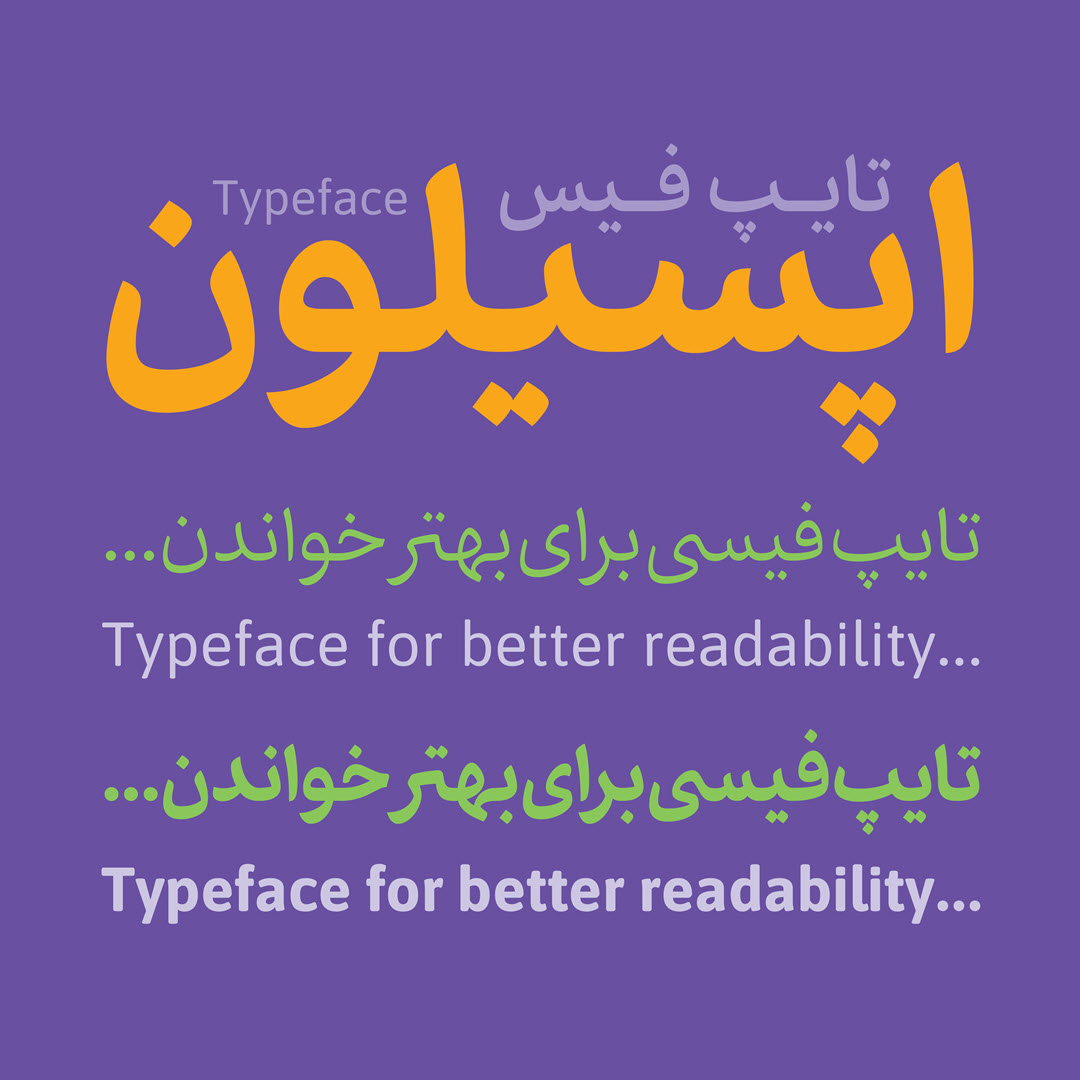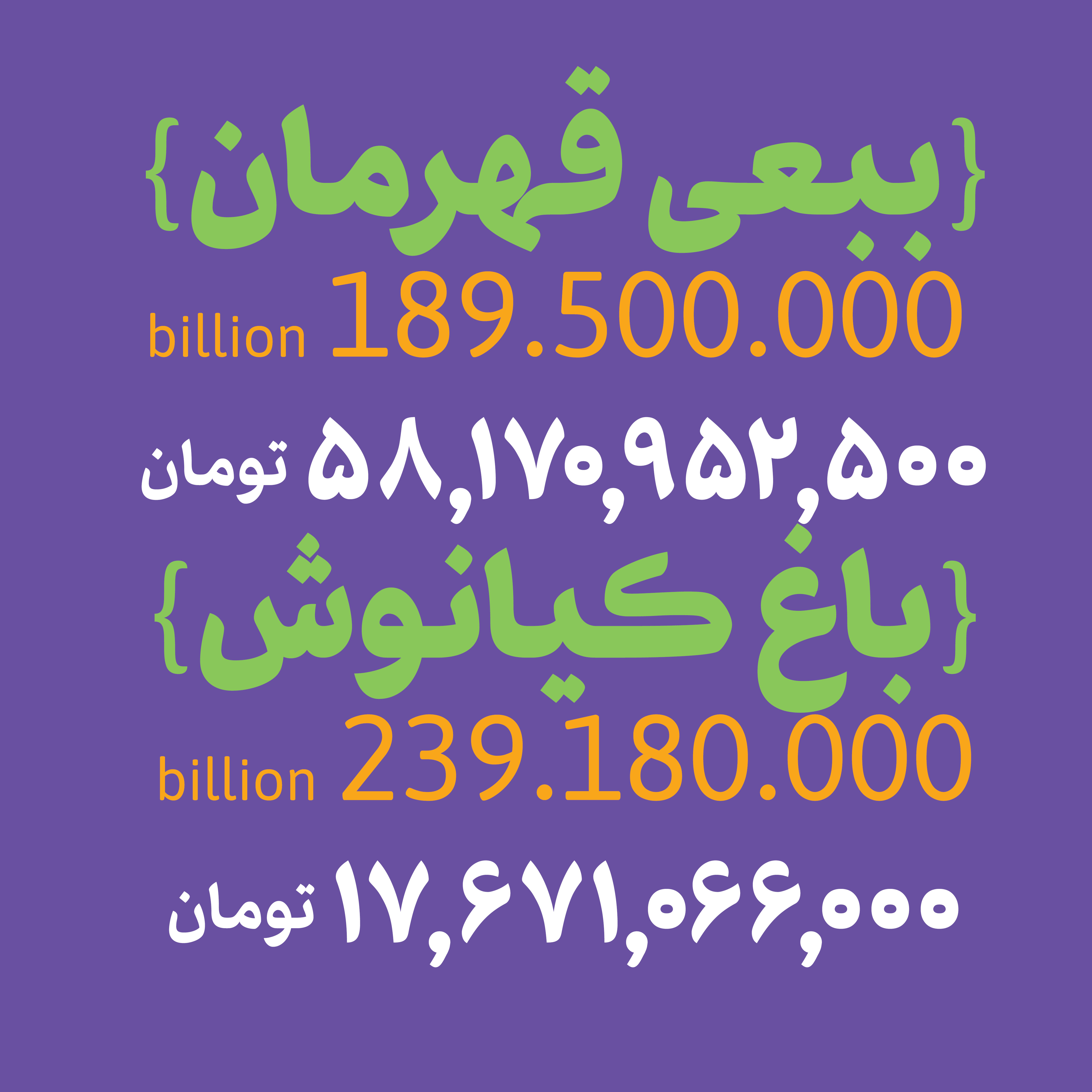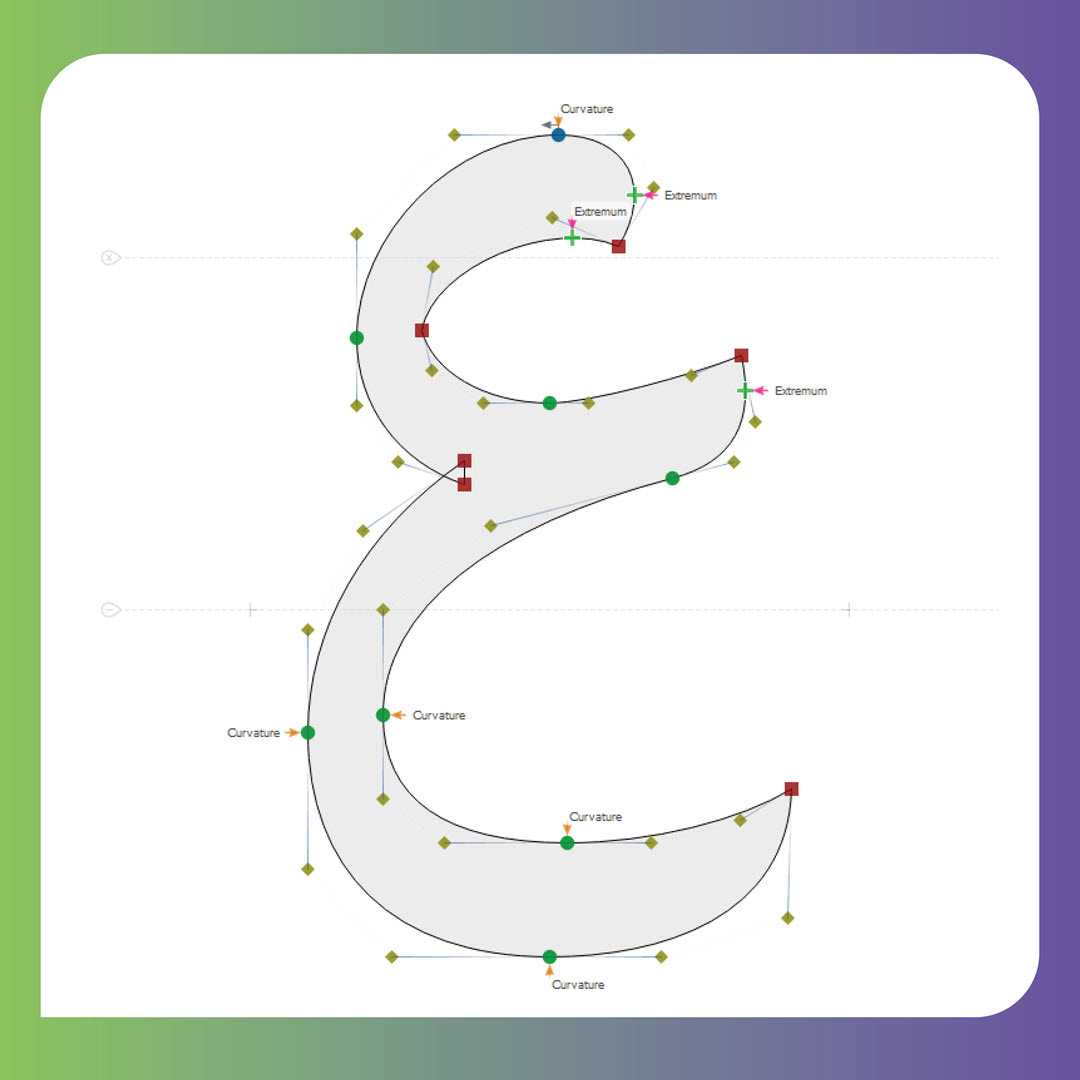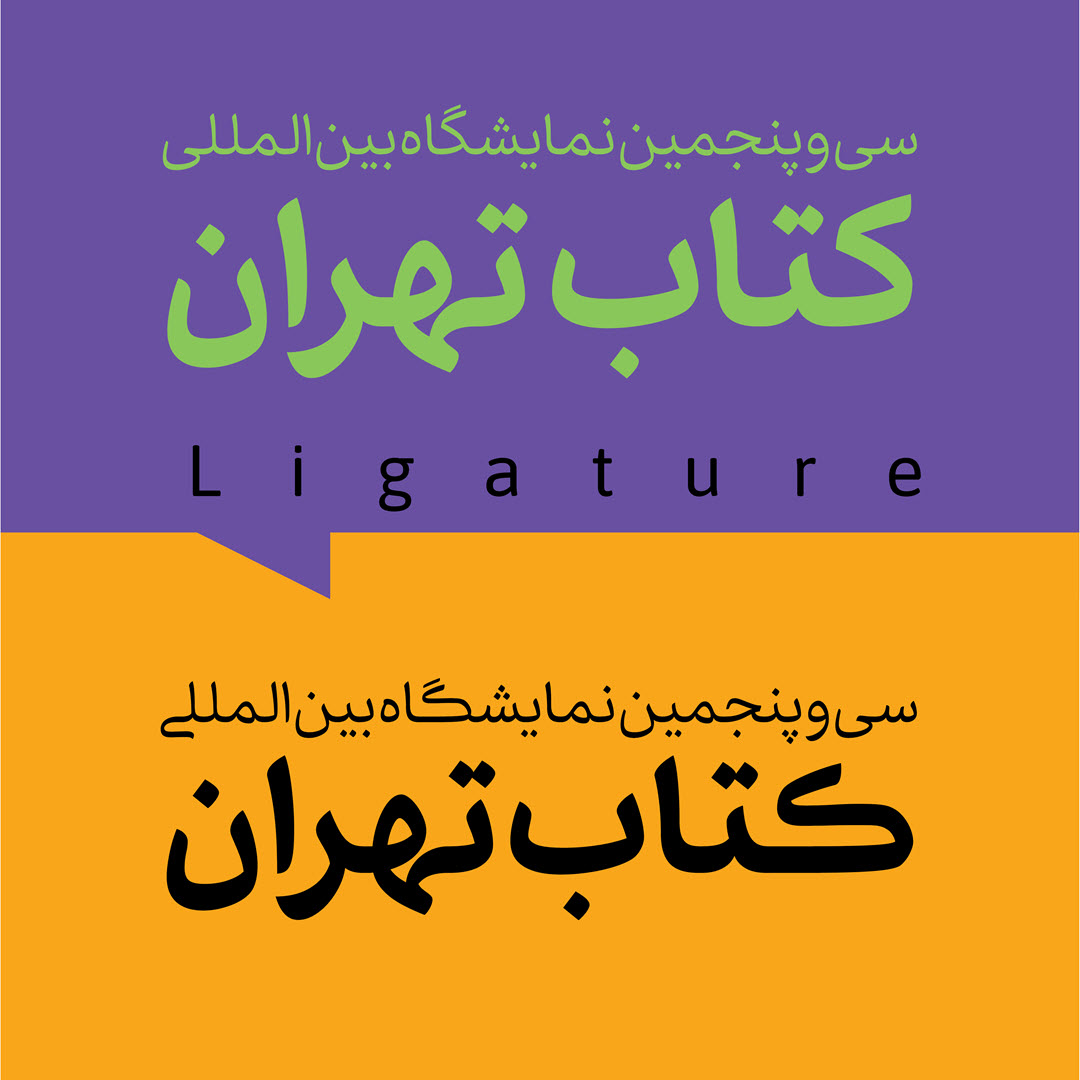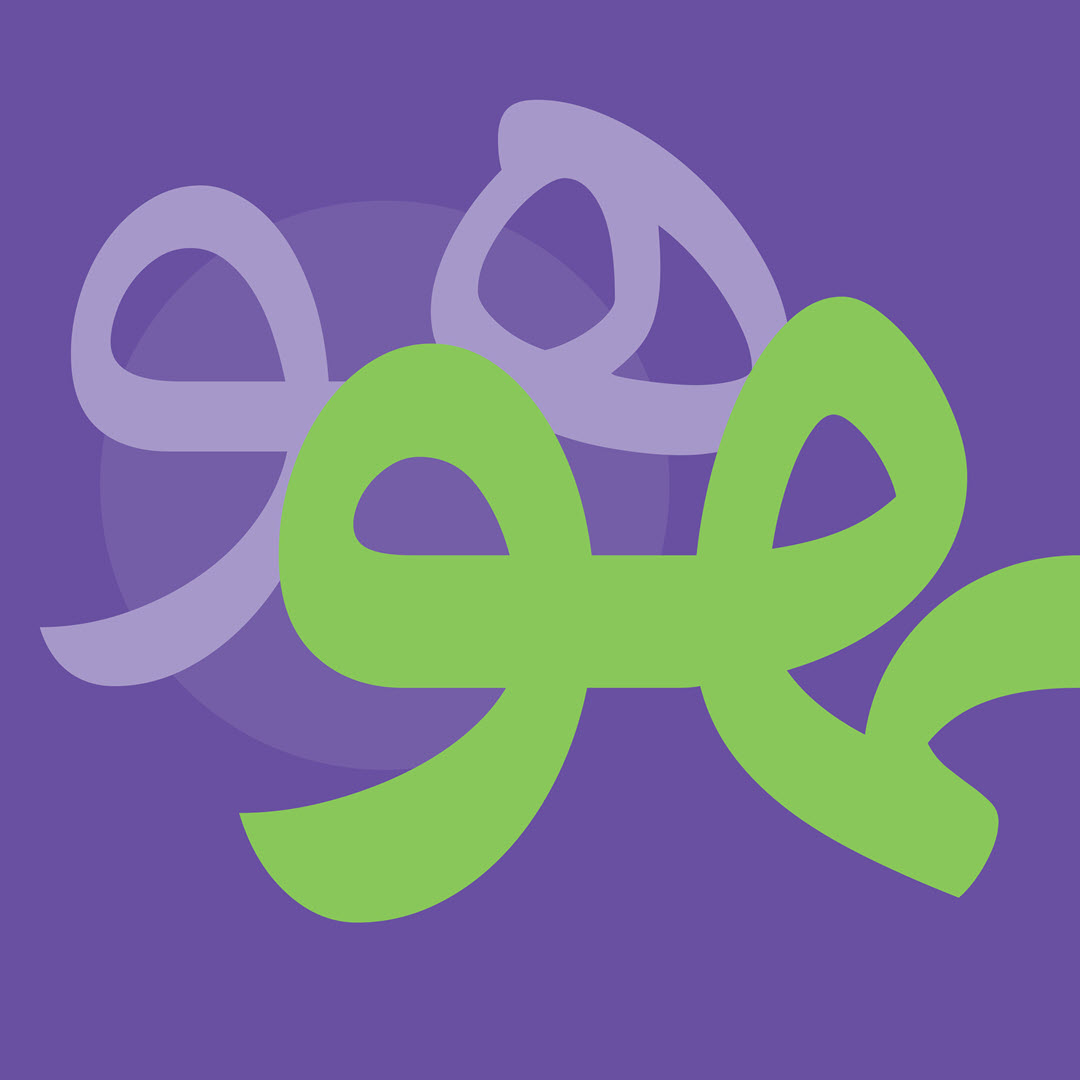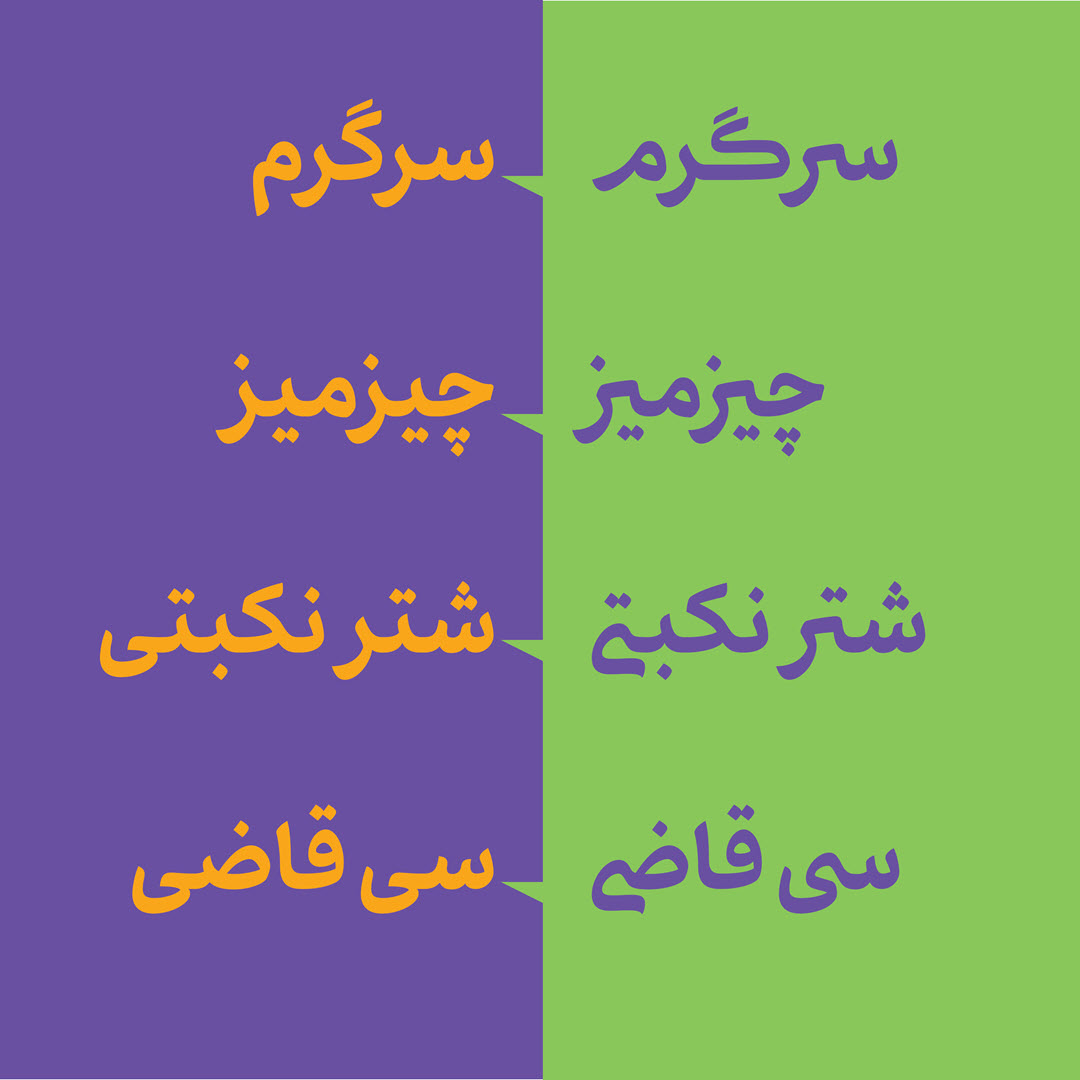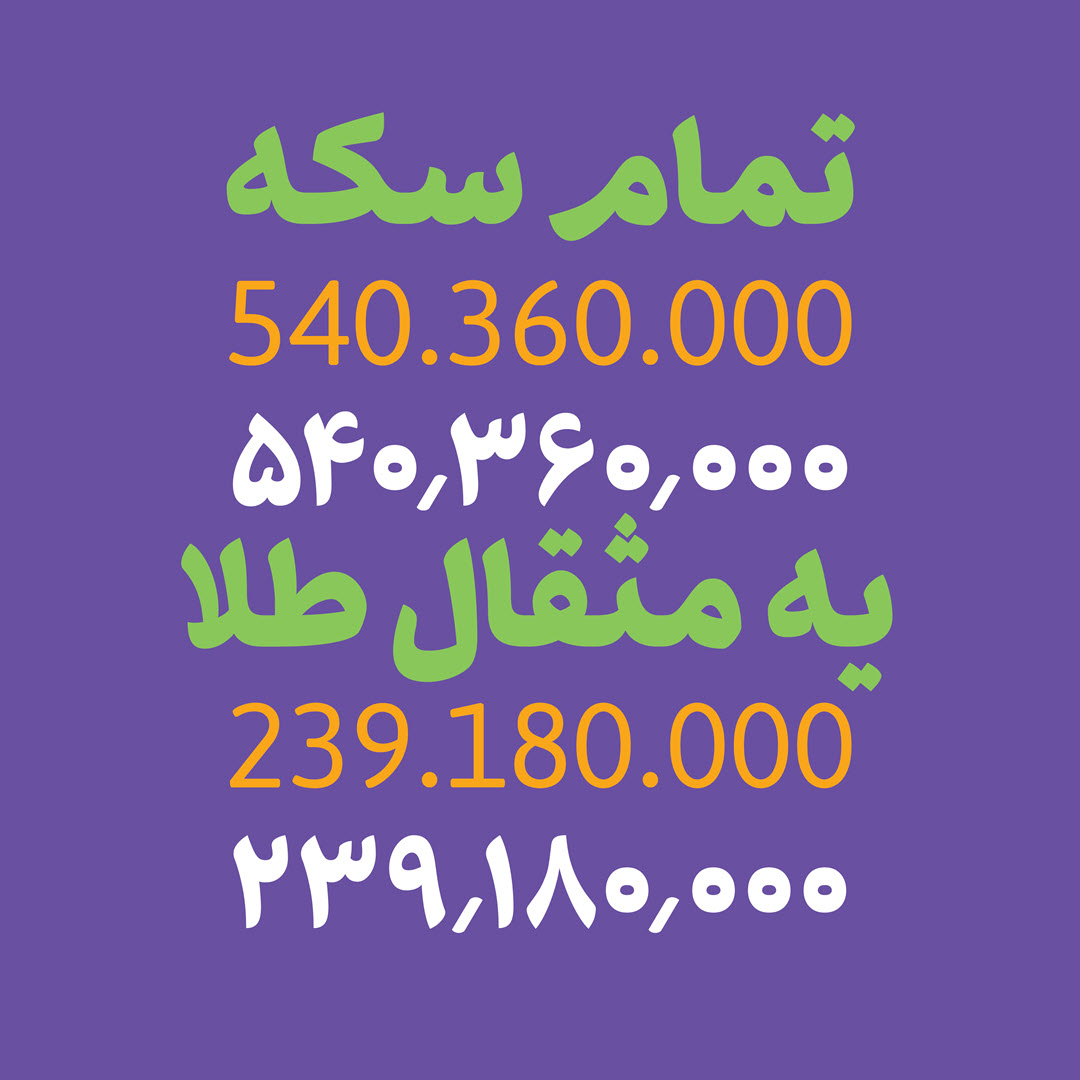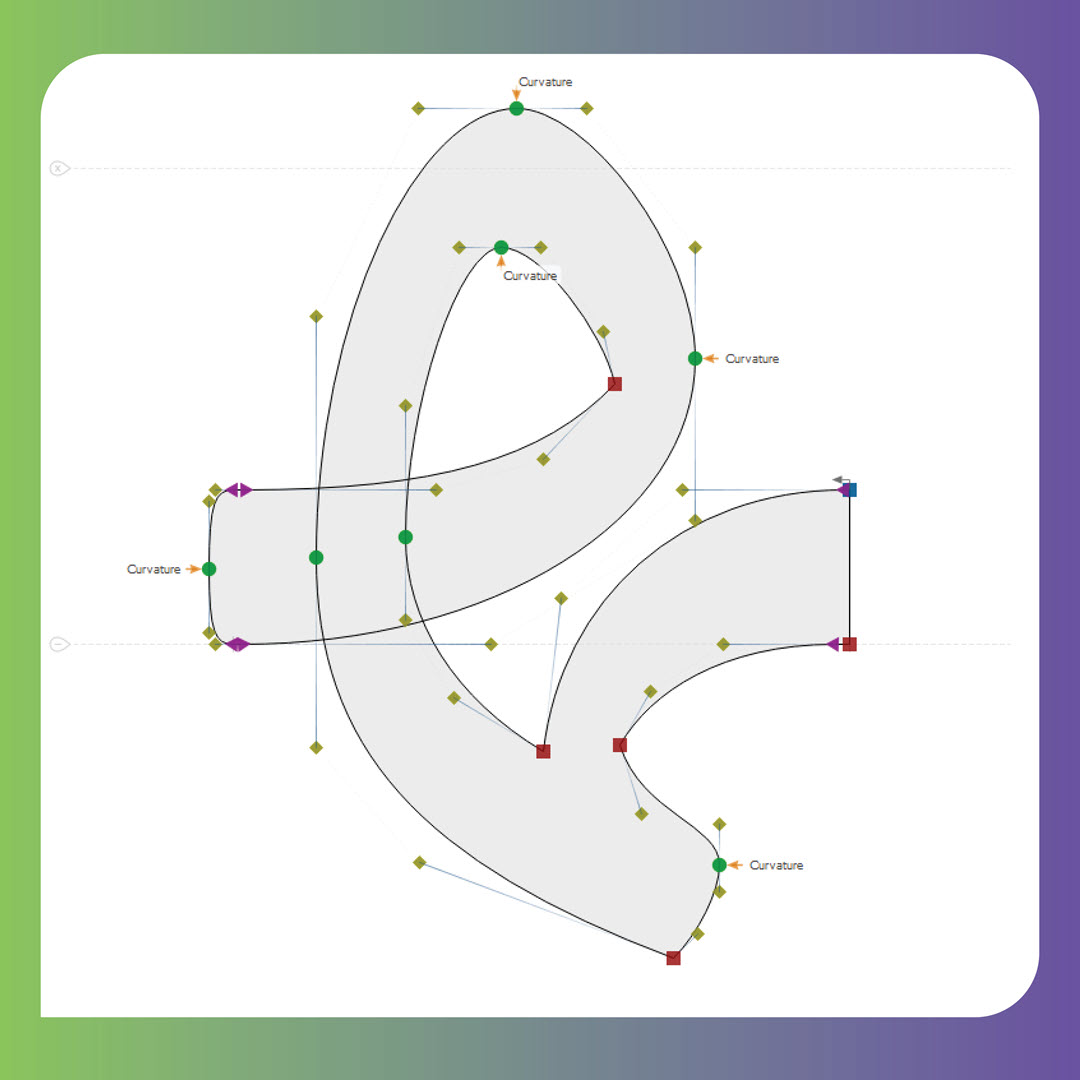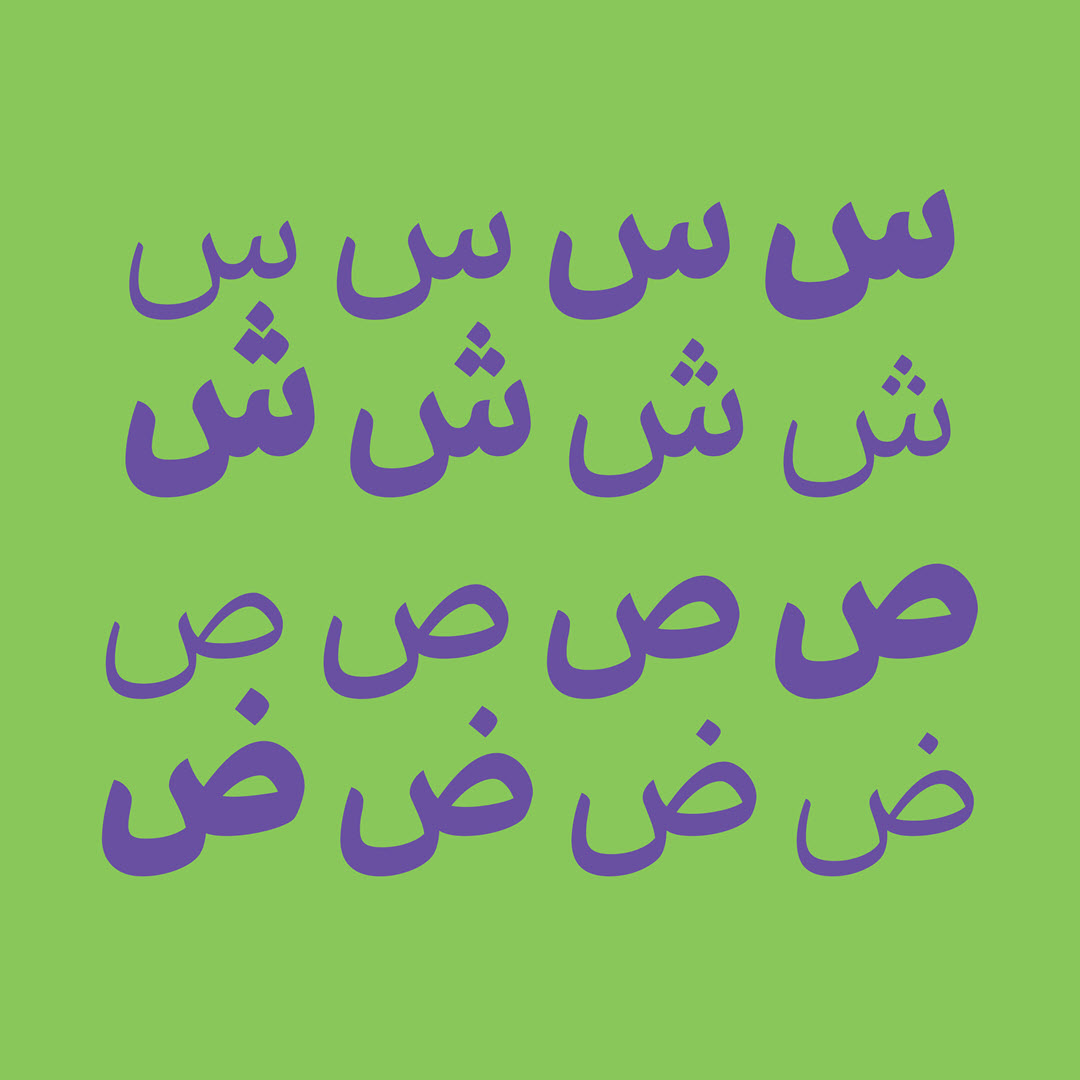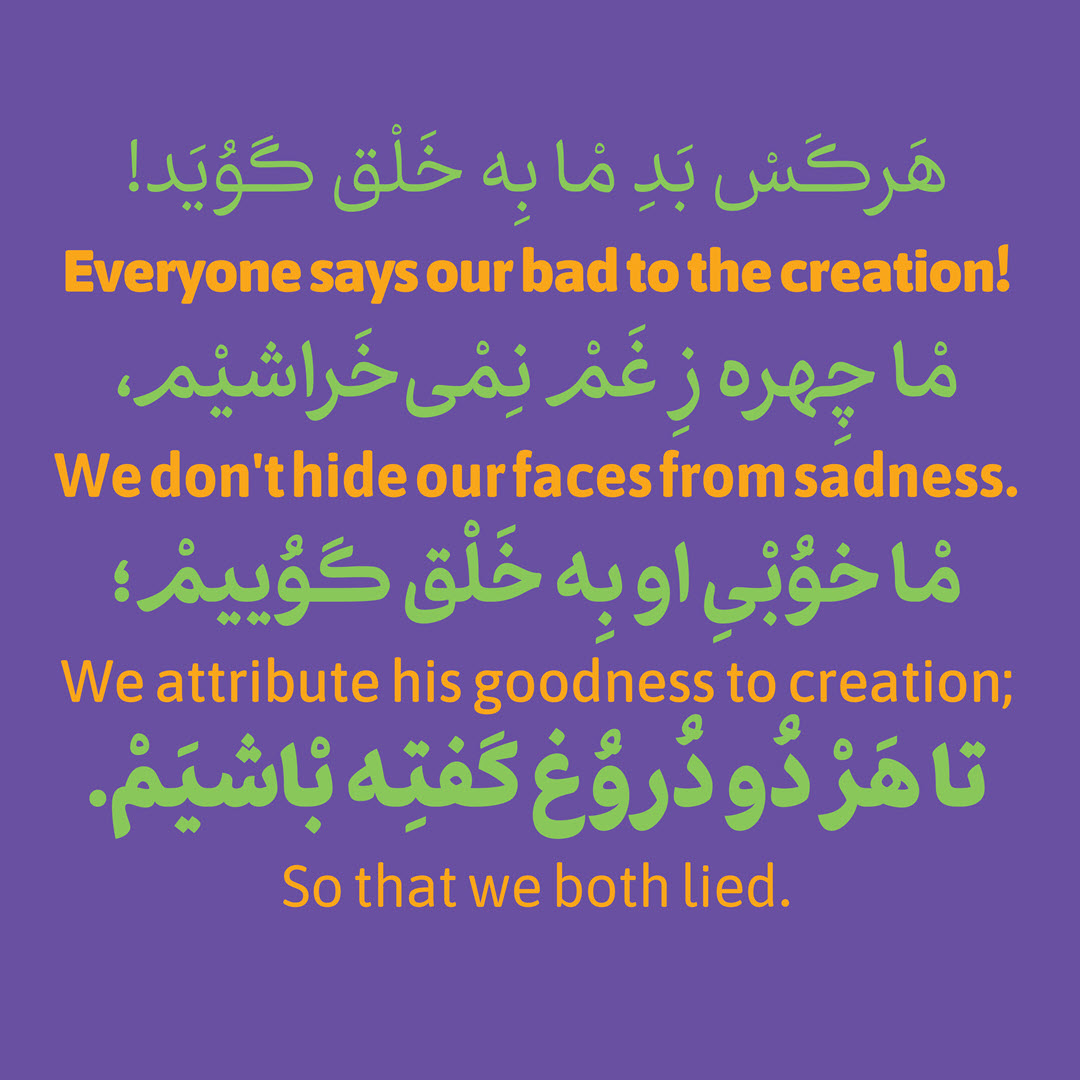
درباره قلم اپسیلون
اپسیلون؛ تایپ فیسی برای خوانایی بهتر...
فونت اپسیلون یک تایپفیس مدرن و منعطف است که با هدف تسهیل در خوانایی متون کتابهای کودک و نوجوان طراحی شده است. این فونت با ترکیب ویژگیهای کلاسیک و مدرن، بهویژه در طراحی فرم حروف، توانسته تعادلی میان زیباییشناسی و کاربردپذیری ایجاد کند.
طراحی اپسیلون، با الهام از خط نسخ و تأکید بر منحنیها و فرمهای نرم، فضایی دوستانه و جذاب برای مخاطبان جوان فراهم میآورد. این در حالی است که وضوح و خوانایی حروف را بهطور قابل توجهی ارتقا میبخشد.
طراحی و ویژگیهای فونت اپسیلون
فونت اپسیلون در چهار وزن مختلف طراحی شده است تا پاسخگوی نیازهای متنوع در نشر کتاب و سایر متون کودک و نوجوان باشد. ویژگیهای منحصربهفرد این تایپفیس، از جمله طراحی منحنیها و فرمهای گرد، نه تنها خوانایی بالایی را فراهم میکند، بلکه حس نزدیکی و ارتباط عاطفی با مخاطب را نیز تقویت میکند.
این فونت بهطور ویژه در متون طولانی، مانند کتابهای آموزشی و داستانهای کودکانه، بسیار کارآمد است. طراحی اپسیلون بهگونهای است که چشم خواننده بهراحتی حروف را دنبال میکند و از خستگی دید جلوگیری مینماید، که این ویژگی برای مخاطبان جوان اهمیت بالایی دارد.
اپسیلون در نمایشگاه هفته تایپ تهران
فونت اپسیلون در اولین نمایشگاه هفته تایپ تهران بهعنوان یکی از آثار منتخب معرفی شد، که این انتخاب نشاندهنده ارزش و تأثیرگذاری طراحی این تایپفیس در صنعت چاپ و نشر است. این موفقیت گواهی بر دقت و کیفیت بالای طراحی اپسیلون است؛ فونتی که نهتنها در حوزه گرافیک، بلکه در کاربردهای حرفهای مرتبط با نشر کتابهای کودک و نوجوان نیز مورد توجه قرار گرفته است.
اپسیلون، انتخابی برای آینده نشر
انتخاب فونت اپسیلون به عنوان یک تایپفیس حرفهای برای کتابهای کودک و نوجوان، گامی مؤثر در ارتقای استانداردهای طراحی گرافیک در این حوزه است. این فونت بهویژه برای کسانی که به دنبال یک تایپفیس خوانا، زیبا و مناسب برای مخاطب نوجوان و جوان هستند، گزینهای بینظیر خواهد بود. علاوه بر این، با توجه به طراحی دقیق و متناسب با اصول خوانایی، اپسیلون میتواند در انواع پروژههای چاپی، دیجیتال و تبلیغاتی مورد استفاده قرار گیرد.
علیرضا پوراکبری